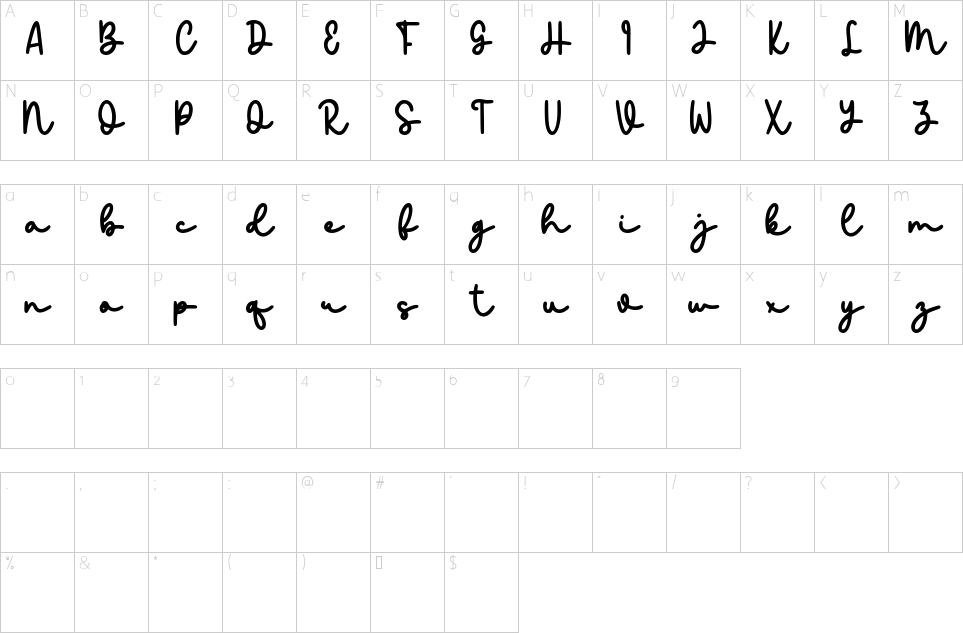
A fonte Minadine é uma escolha perfeita para os designers que buscam uma combinação harmoniosa e sofisticada de estilos. Desenhada pela Essentials Studio, esta fonte está disponível gratuitamente tanto para Windows quanto para Mac, permitindo que designers de todo o Brasil procurem uma opção de fonte para seus projetos sem custos. Com seu design cuidadosamente elaborado, a Minadine oferece um toque elegante e versátil que se adapta perfeitamente a diversas aplicações, desde gráficos para o marketing até textos em aplicativos móveis. Com apenas 1,466 downloads, a Minadine está crescendo em popularidade, mostrando que a qualidade e simplicidade desta fonte estão ganhando espaço no mercado de recursos gráficos. Download agora a Minadine e transforme seus projetos de uma forma única e profissional.